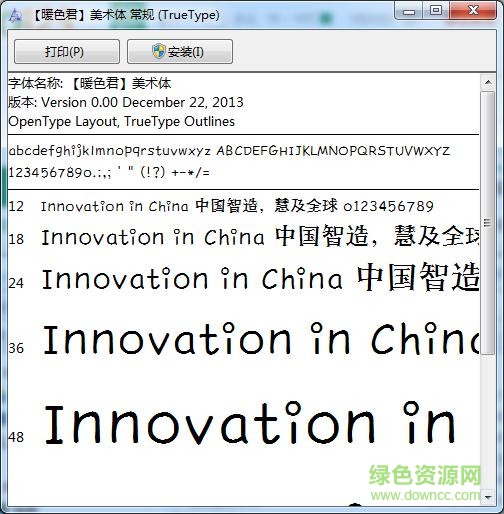
暖色美術(shù)體
暖色美術(shù)體是一款非常有個(gè)性的美術(shù)字體,可以運(yùn)用到比較廣泛的區(qū)域,使相同的應(yīng)用產(chǎn)生不同的效果,最新最全的英文,簡繁體字庫,輕輕松松換字體,簡簡單單換心情,個(gè)性由自己主宰!
暖色美術(shù)體是一款用于美工設(shè)計(jì)方面的字體,該字體瀟灑俊逸、自然舒展、賞心悅目,看上去十分美觀,整體效果非常統(tǒng)一,且字庫完整,可以廣泛應(yīng)用于名片設(shè)計(jì)、新聞媒體、宣傳海報(bào)、ppt、影視制作以及任何使用文字的領(lǐng)域。